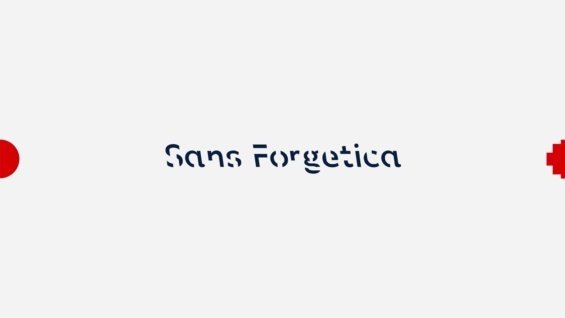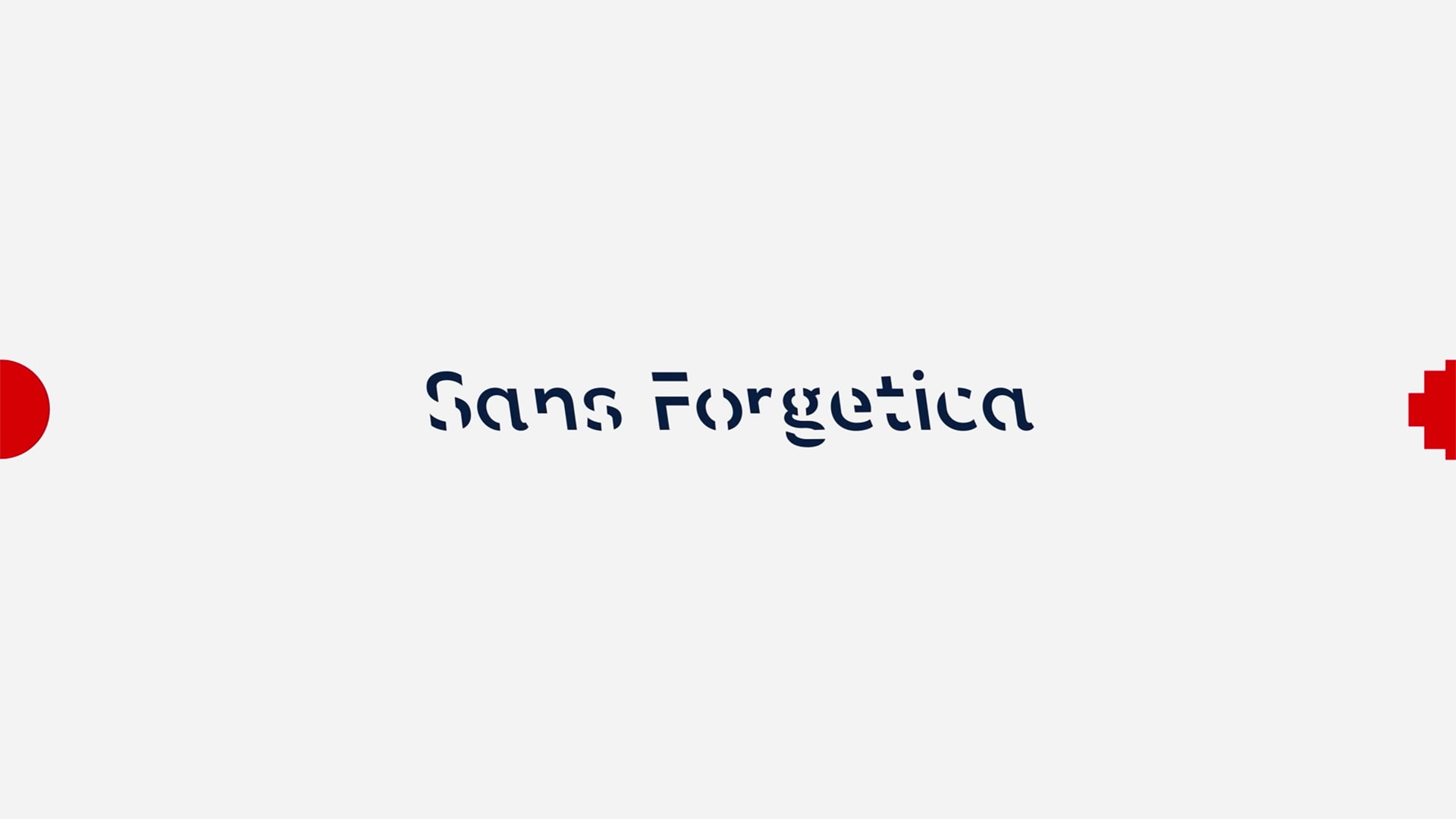
A quanto pare i font non devono essere solamente belli da vedere ma anche funzionali. Talvolta la parte estetica può essere quasi omessa se il fine è un altro. È il caso di Sans Forgetica, un’incredibile font studiato appositamente per chi legge, affinché ricordi ciò che ha letto.
L’idea del font e lo studio
Sans Forgetica è stato realizzato dai ricercatori del Royal Melbourne Institute of Technology, partendo dall’idea di base di un professore universitario. L’idea è stata poi accolta dai designer della School of Design e dagli scienziati comportamentali del Behavioural Business Lab. e si basa sul principio della difficoltà desiderabile.
Il team ha realizzato diversi font e li ha messi alla prova testandoli su un campione di 400 studenti. Sans Forgetica è risultato essere il più efficace di tutti, per lo scopo per il quale era stato creato.
Così i ricercatori hanno pubblicato il nuovo carattere tipografico che aiuta a memorizzare meglio ciò che si legge e lo hanno distribuito gratuitamente, ma attenzione: non fa miracoli!
Sans Forgetica e la difficoltà desiderabile
Come detto il nuovo font si basa sul principio della difficoltà desiderabile, ma cosa vuol dire? Si è appreso che nell’imparare e nel memorizzare è meglio incontrare degli ostacoli, non troppo grandi e insormontabili, perché la fatica, se non eccessiva, ci stimola e ci aiuta a ricordare meglio.
Seguendo questo principio Sans Forgetica è stato reso volutamente difficile da leggere. Il font, a differenza dei suoi “colleghi” che vanno di moda oggi, non è pulito e liscio, si basa, invece, su principi quali il blackslant e l’incompletezza delle lettere.
Il blackslant vuol dire che il testo è piegato nella direzione opposta rispetto al corsivo ordinario, ovvero ha una leggera pendenza verso sinistra. Mentre le lettere incomplete fanno si che sia il cervello a doversi sforzare per completarle. Il grado di difficoltà aggiunto da Sans Forgetica alla lettura migliora l’elaborazione cognitiva e la memorizzazione.
I successi di Sans Forgetica
Tuttavia non bisogna esagerare con la difficoltà. I font in esame erano, infatti, tre. Sans Forgetica ha vinto perché era la giusta via di mezzo tra uno e l’altro. Uno dei font testato dai 400 studenti è risultato essere troppo complicato da leggere, mentre l’altro troppo semplice.
Sans Forgetica ha, invece, ottenuto ottimi risultati. Sembrerebbe, infatti, che i livelli di memorizzazione di un test normale si assesterebbero al 50%, mentre questo font ha raggiunto il 57%.
I creatori hanno però spiegato che Sans Forgetica deve essere usato con moderazione: “Non è fatto per leggere dei romanzi, perché in quel caso farebbe solo venire dei potenti mal di testa. Serve per evidenziare un passaggio chiave, come una definizione, non per altre cose”. Ad esempio potrebbe tornare utile, spiegano, a chi sta cercando di imparare una lingua straniera.